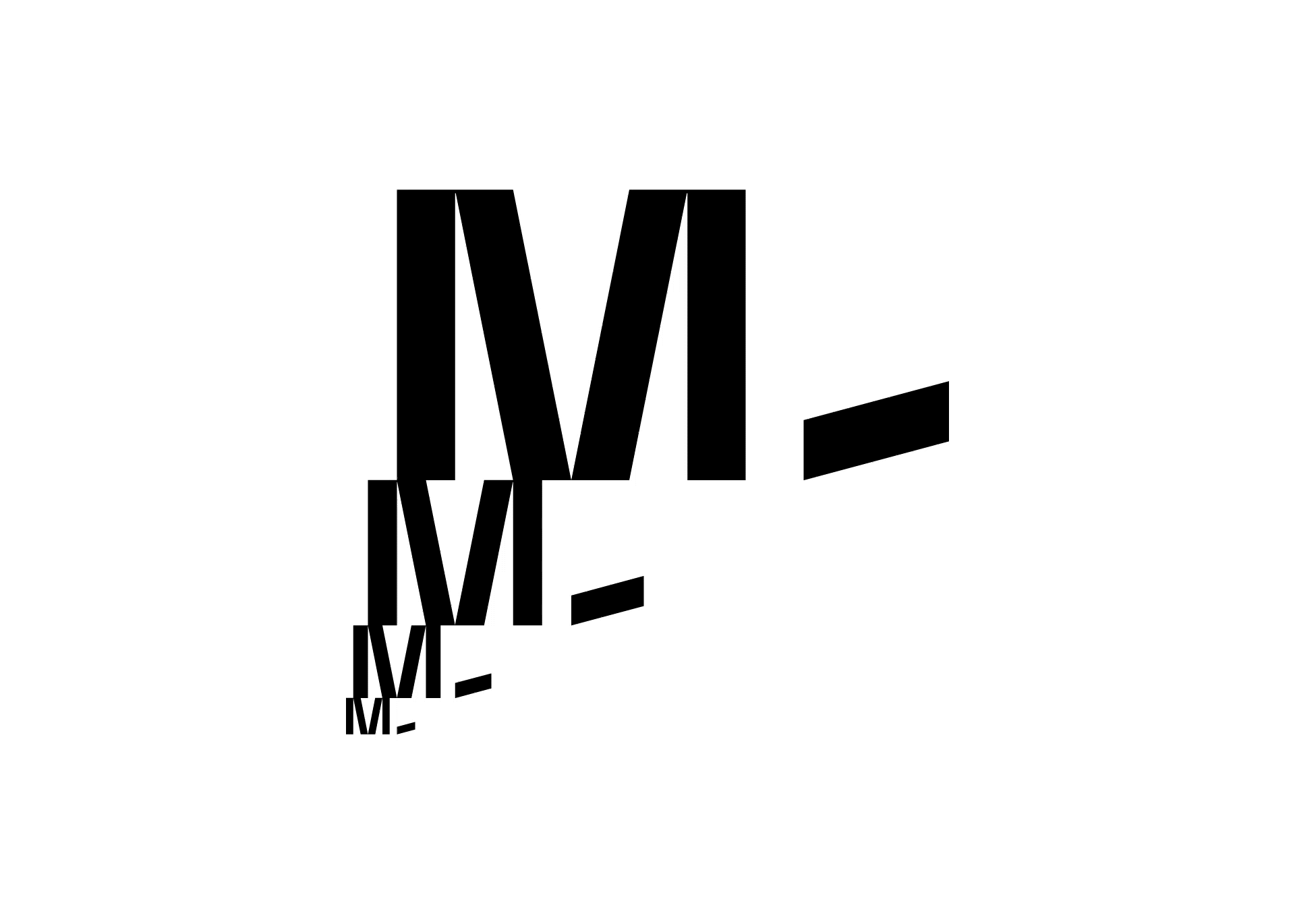
M Capital
M Capital, investisseur atypique, a renouvelé son identité visuelle avec audace pour refléter son esprit chic, accessible et engagé dans l'avenir.
Société indépendante de capital investissement, immobilier et dette privée, M Capital a, depuis sa création en 2002, connu un développement qui le classe parmi les 300 premières entreprises de croissance européennes (Financial Time Fast 500). Avec plus de 510 M€ d’actifs gérés pour le compte de grands investisseurs institutionnels et plus de 27 000 investisseurs privés, la société est devenue l’un des principaux investisseurs privés français. Implantée principalement à Toulouse et Paris, c’est aussi une marque qui se définit comme « chic et accessible », « rock et bienveillante », et cultive dans la sphère financière un état d’esprit particulier, à la fois sérieux et respecté, libre voire impertinent. Cette société atypique et reconnue, impliquée notamment dans la réflexion sur les grands sujets d’avenir et la ville de demain, nous a mandaté en 2019 pour repenser intégralement son identité visuelle.
Nous avons d’emblée souhaité éviter de se conformer à l’esthétique classique des sociétés de finance, tout en développant un socle visuel solide et sérieux. Notre axe de travail s’articulant autour du mantra « Amplifier l’extraordinaire », une promesse emphatique et volontairement démesurée, nous avons contruit une identité typographique empreint de clarté et de radicalité. Le logo, un dessin typographique stable et structuré, révèle quelques bizarreries qui apportent la juste dose de singularité. Une palette de couleurs vives permet d’offrir des contrastes forts sur les différentes déclinaisons.
L’empreinte visuelle se construit ensuite autour du monogramme « M-« , qui, par un jeu d’échelles, vient illustrer la promesse de croissance et de progrès. Un jeu de construction qui permet de créer à l’infini des motifs graphiques et unifier les différentes prises de parole.